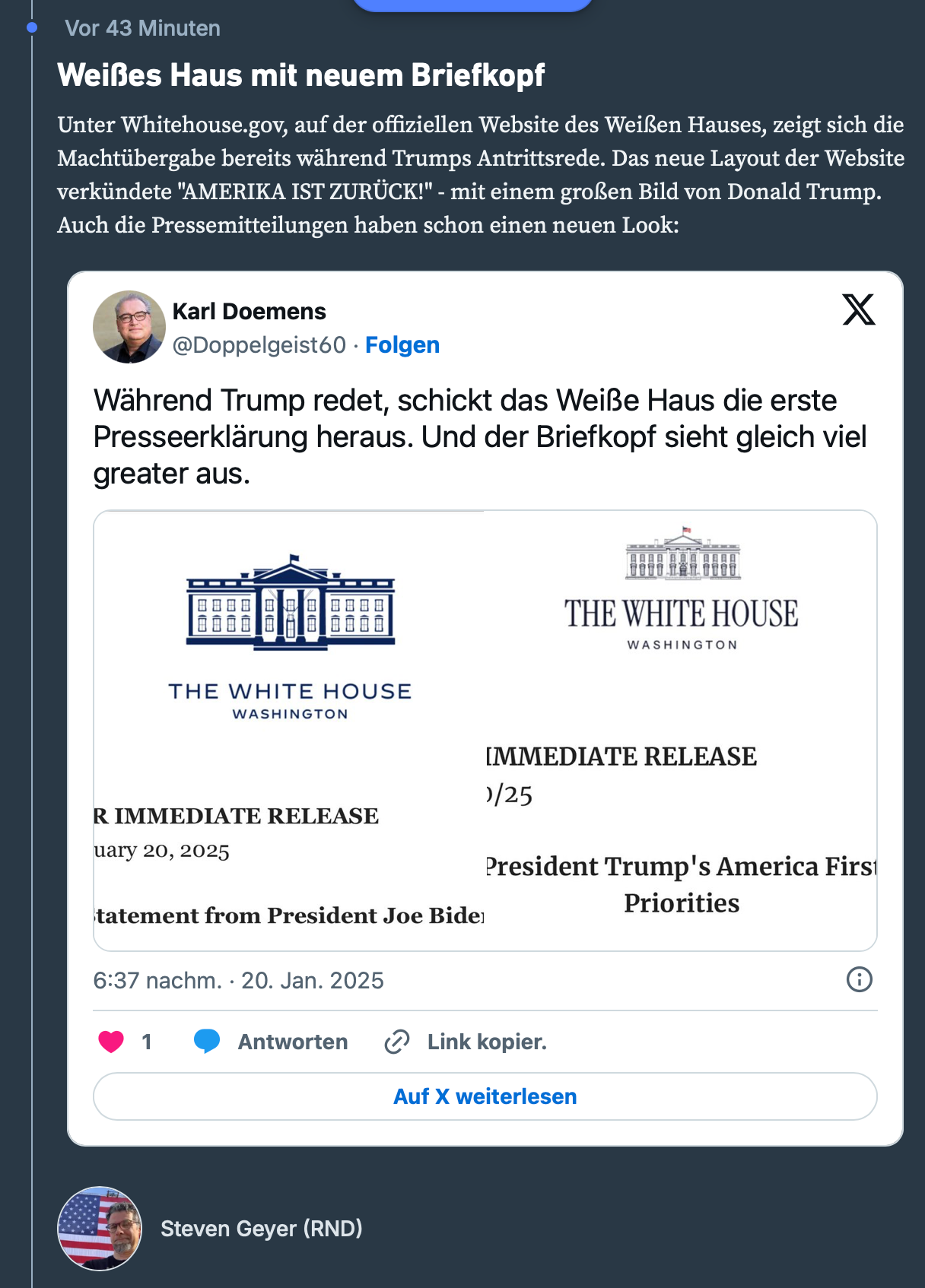
Hmmm, typografisch betrachtet not so great – was sagt Ihr?
Grafisch auch nur unterhalb von mittelgut ...
Davon wollte ich gar nicht erst anfangen, aber ja: Du hast recht!
Zurück in die Zeit von Clipart und Wordart.
Lustig, ich dachte an eine kaputtgezogene ITC Garamond (war mal Apples Markenschrift). Aber passt ja zum globalen Rechtsruck, dass wir auch graphisch zurück in die gute alte Zeit kommen.
Schlecht ist das neue gut.
Nix Garamond, wobei Renaissance (Wiedergeburt) ja irgendwie passen würde. Das dürfte allerdings ein Google-Font sein: Instrument Serif.
Auf dem alten Briefkopf ist die Decimal.
Naja wenigstens handwerklich darauf achten dass die Strichstärke in der Schrift optisch die Bildmarke auffängt. Also mit einer feineren Darstellung in der Bildmarke arbeiten damit das alles nach einem Guss aussieht. So hätte ich es gelöst.
Wie würde ein Entwurf aussehen, den Du als harmonisch empfindest?
Auf jeden Fall weg von All Caps, bei beiden Entwürfen. Und bei dem Briefkopf des Weißen Hauses von el presidente irgendwie mehr Luft. Weniger zusammengedrängtes Schwarz. Das simplifizierte Erscheinungsbild von Bidens Haus gefällt mir besser, die US-Flagge bei el presidentes hingegen ist ein nettes Detail.
Die Type in der letzten Legislatur würde ich lassen. Die Bildmarke von der neuen würde ich übernehmen ein wenig vereinfachen und Linien stärker und daraus wäre eine schöne Weiterentwicklung geworden. Thematische Spielereien mit dem Logo würde ich nie empfehlen.
Wirklich? Auf mich wirkt das wie arg verkleinerte Clipart. Wenn man das vereinfacht und die Linien stärker macht, gelangt man doch irgendwie wieder zur vorigen Bildmarke …
Die Außenform ist bei der neuen besser getroffen. Wie gesagt Details rausnehmen dadurch wirkt das aber leichter und nicht so blockig wie die vorherige Variante. Sieht mir zu gewollt ikonographisch aus. Das zu reduzierte ist für mich im Moment das neue 2025 Clipart.
So richtig erhaben und hoheitlich wirken die Bilder alle nicht. Ich kenne mich aber nicht aus mit den Sehgwohnheiten in USA.  Selbst die reduzierteren Zeichnungen (Biden) zeigen dann doch wieder jede Fenstersprosse. Das empfinde ich als unstimmig.